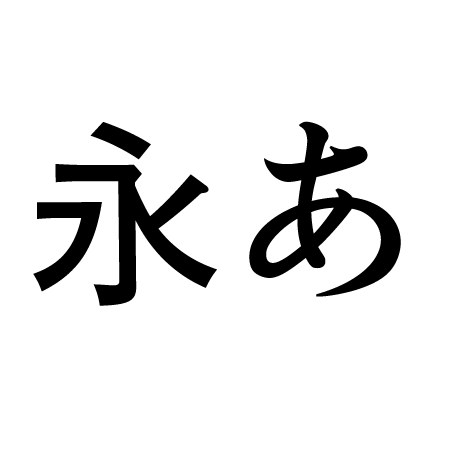
モトヤアンチック3
サブスタイルシリーズは、様々な場面や媒体の雰囲気に合わせて書体を選択できるように、従来の明朝体・ゴシック体・丸ゴシック体の仮名デザインを変更した派生書体です。
その中でも、アンチック体は、ゴシック体の漢字と明朝体の仮名を組み合わせた書体となっており、漫画でのキャラクターのセリフ・ふきだし箇所でも、その漫画の世界観や場面の雰囲気を壊すことなく自然なイメージで使用できます。